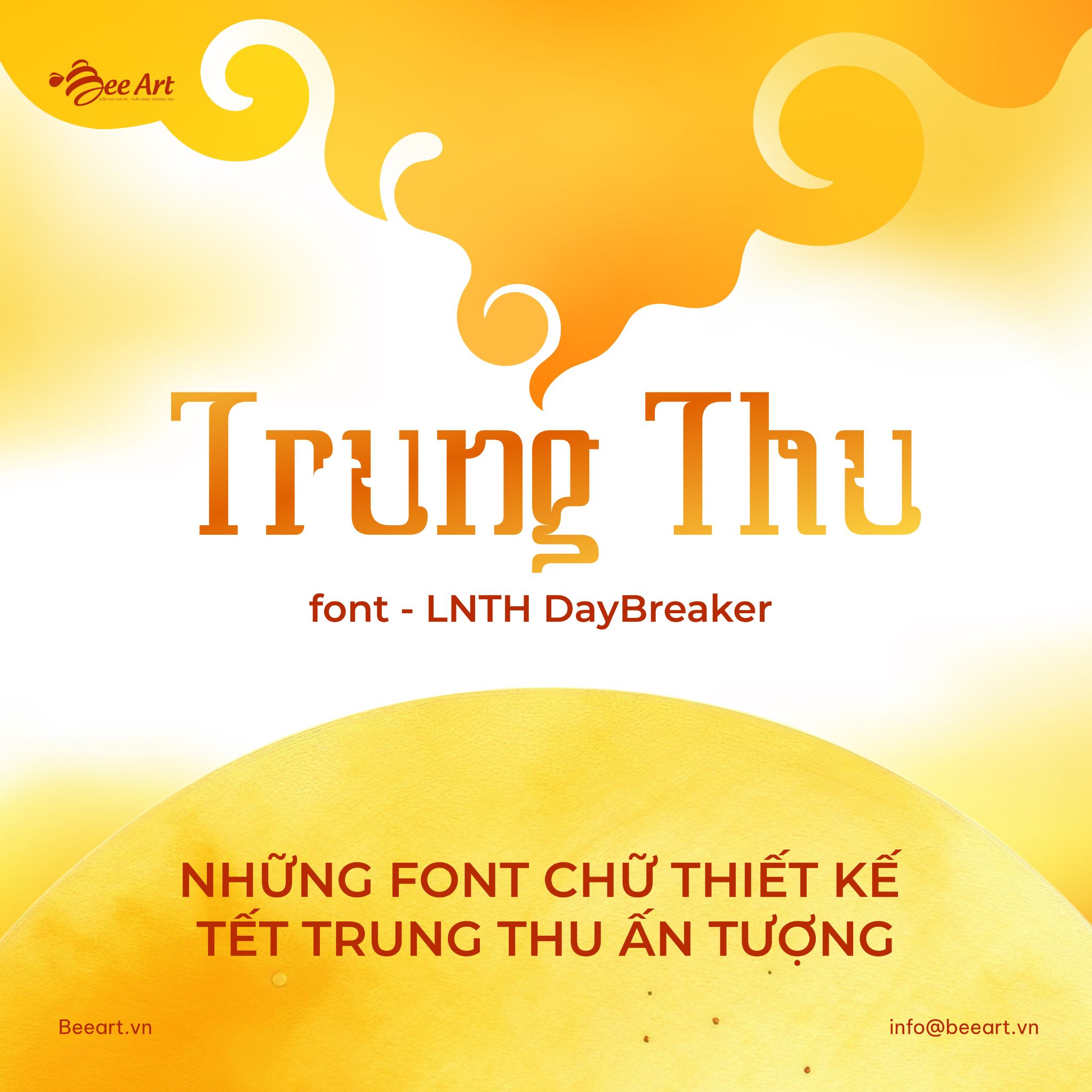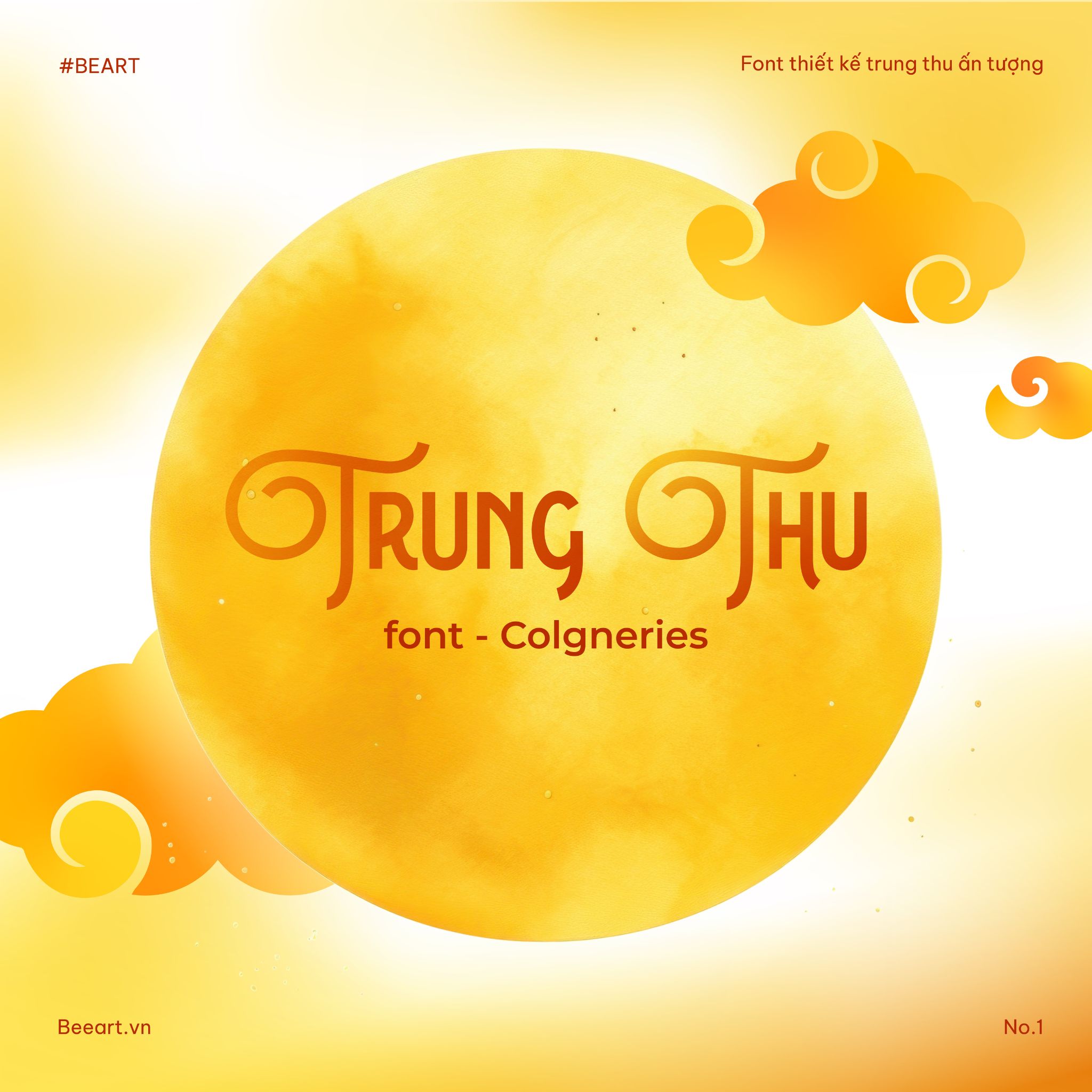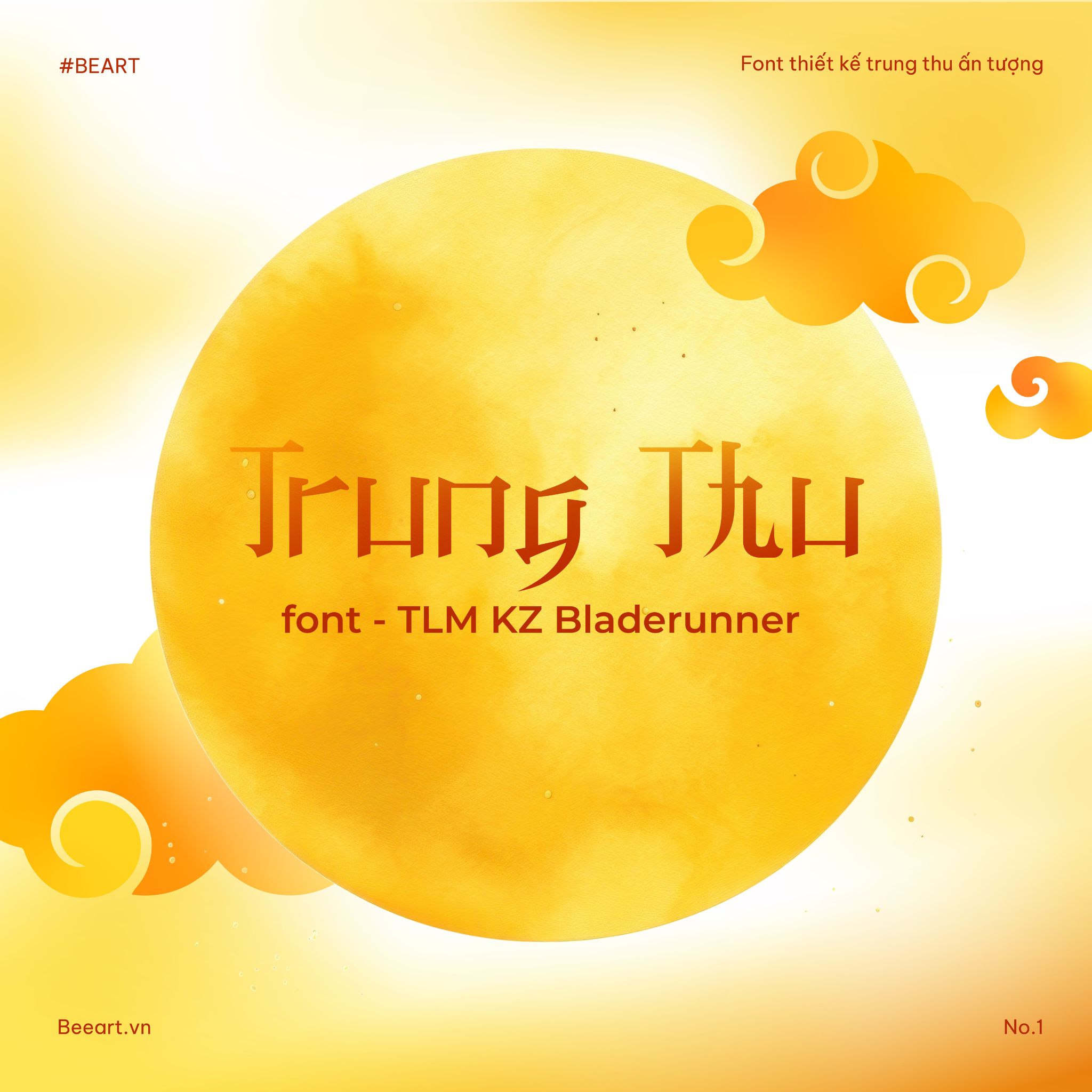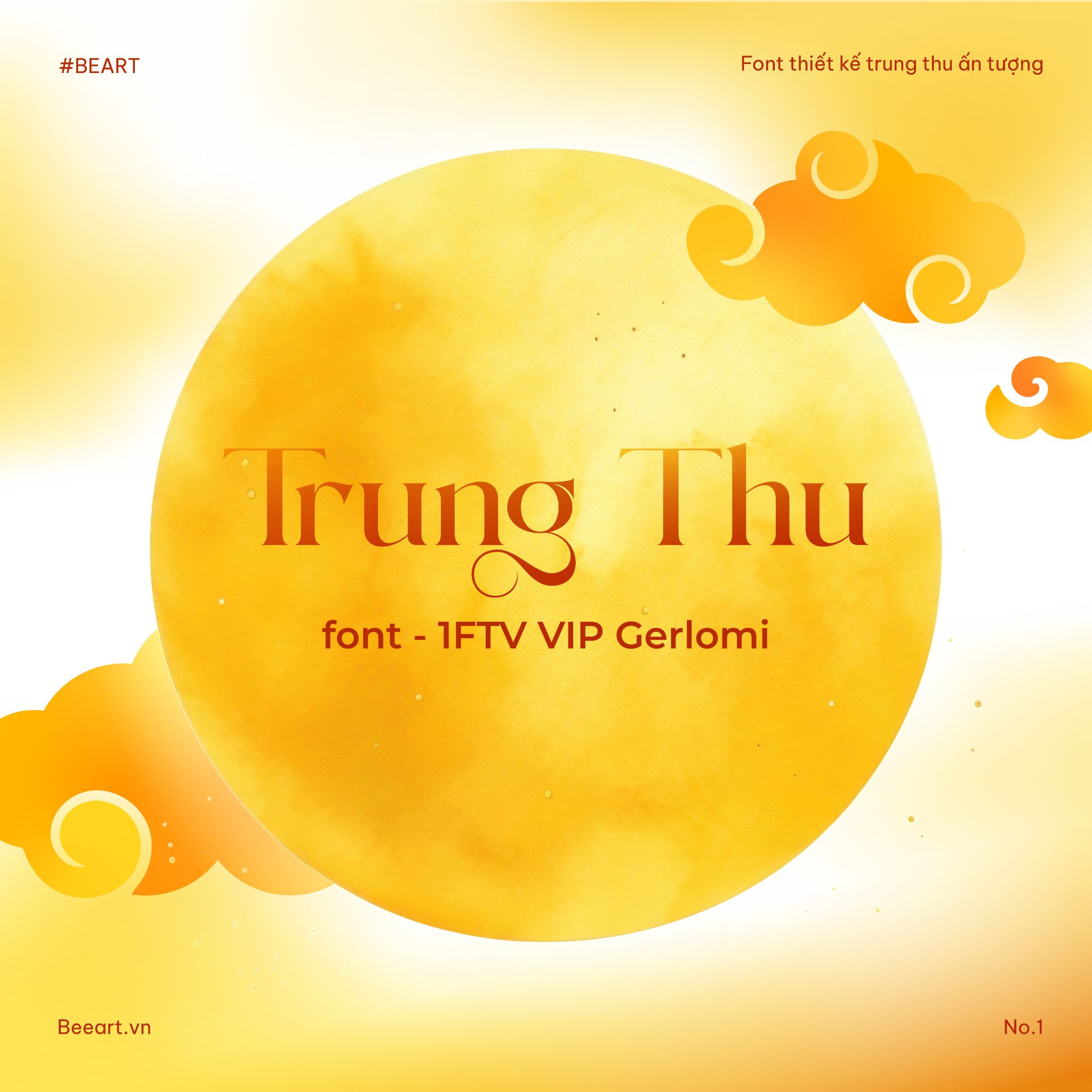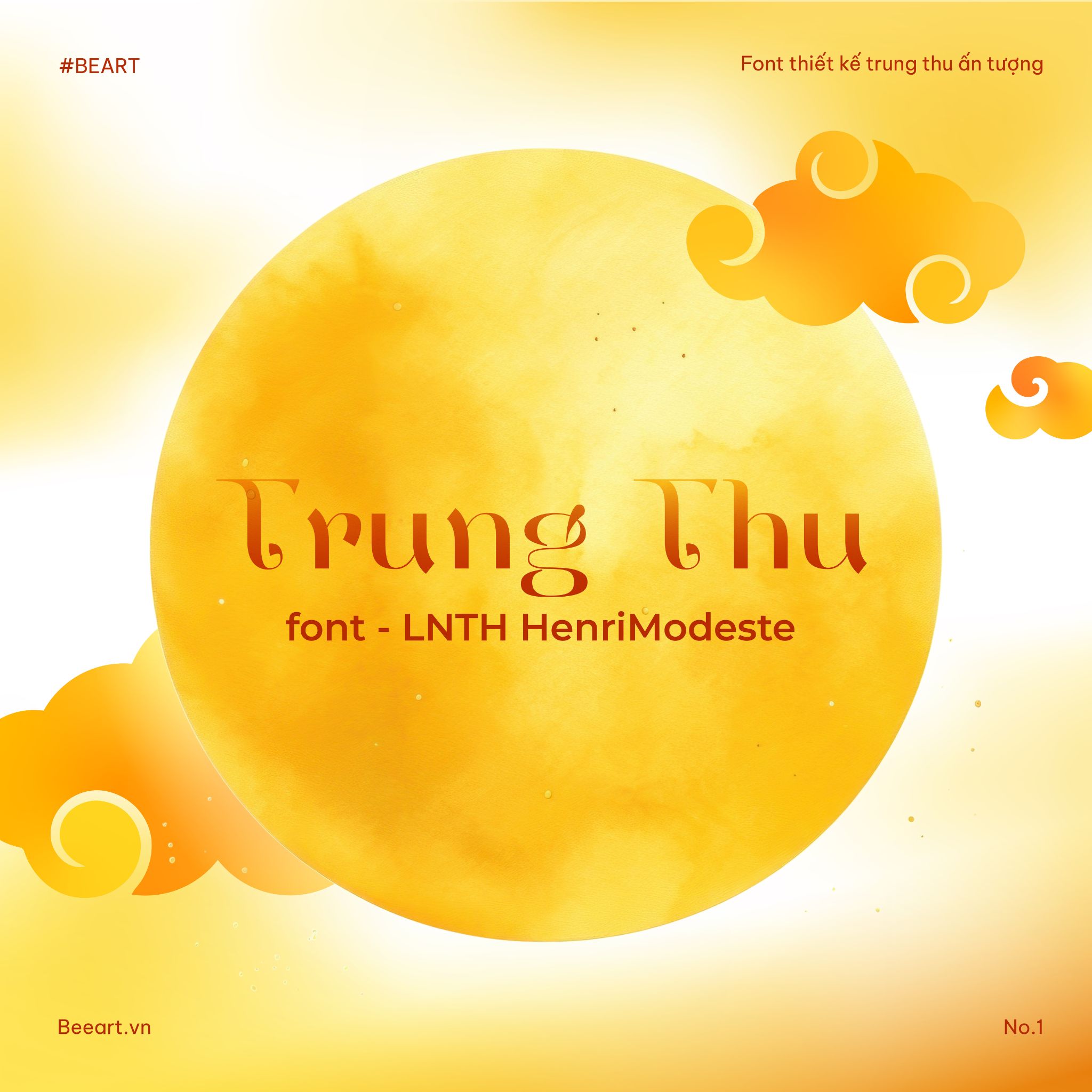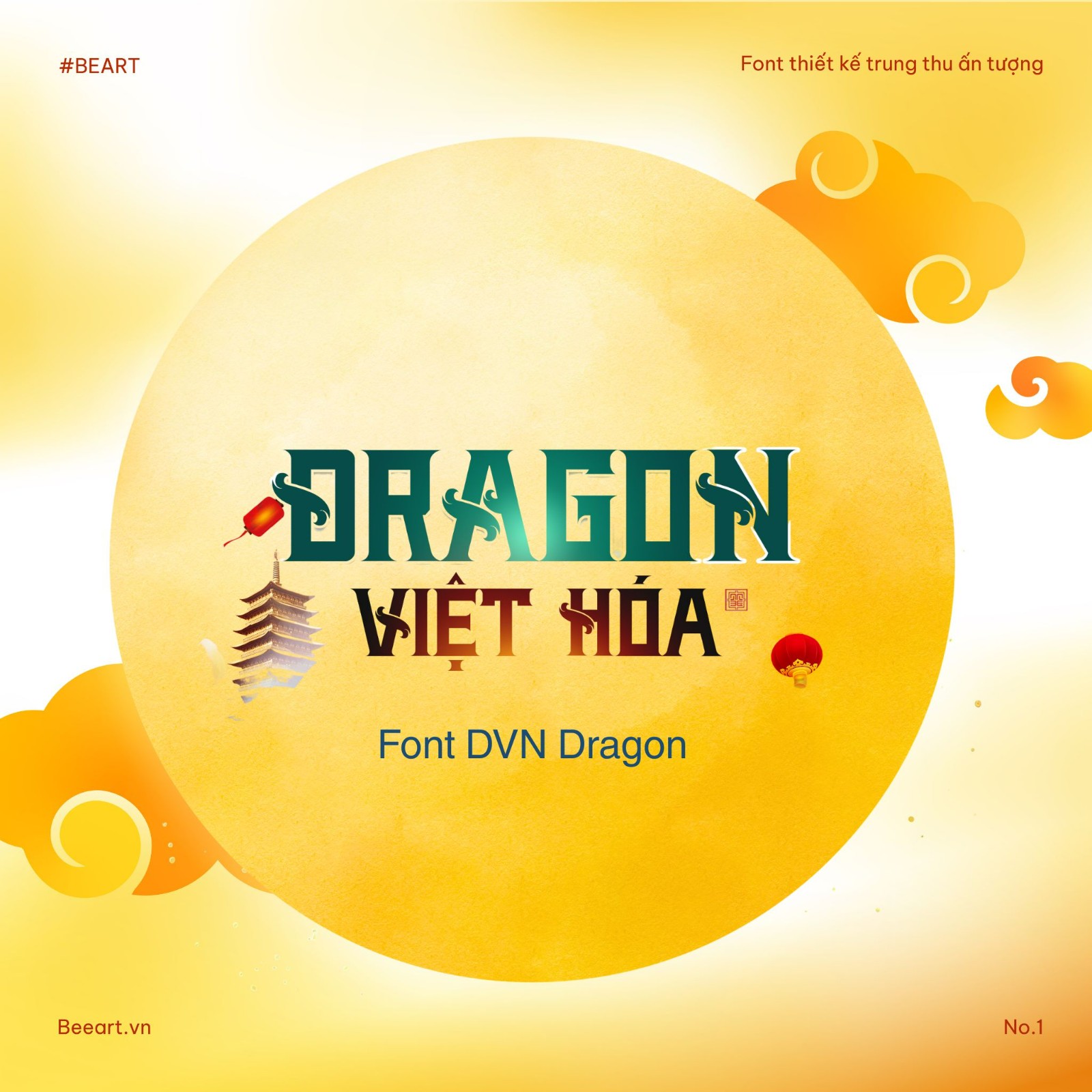
Mách bạn 11 font chữ thiết kế bao bì Tết Trung thu cực đẹp
Những font chữ thiết kế bao bì Tết Trung thu đẹp và ấn tượng như LTNH DayBreaker, Colgneries,... sẽ là những lựa chọn cứu cánh designer cho mùa trăng năm nay.
Font chữ thiết kế bao bì Tết Trung thu
Trung Thu đang đến rất gần rồi, các designer đã chuẩn bị ý tưởng cho mùa trăng năm nay chưa? Nếu bạn vẫn còn băn khoăn trong việc lựa chọn font chữ phù hợp cho những thiết kế bao bì hay ấn phẩm Trung thu, thì đây chính là gợi ý dành cho bạn. Hãy cùng Bee Art khám phá 11 font chữ Việt hóa độc đáo giúp thiết kế bao bì Tết Trung thu của bạn nổi bần bật trên mọi mặt trận.
Lưu ý khi chọn font chữ thiết kế bao bì Tết Trung thu 2025
Không khí mùa Tết Trông Trăng đang dần nhộn nhịp, và đây cũng là lúc các thương hiệu đẩy mạnh ra mắt sản phẩm quà tặng cùng nhiều hoạt động truyền thông nổi bật. Một trong những yếu tố quyết định sự thành công của bao bì chính là font chữ - chi tiết nhỏ nhưng có sức ảnh hưởng lớn đến cảm nhận của khách hàng. Để thiết kế vừa đẹp vừa hiệu quả, bạn cần lưu ý một số điểm sau khi lựa chọn font chữ.
Phân cấp rõ ràng giữa các nhóm thông tin
Khi thiết kế bao bì Tết Trung thu, không phải nội dung nào cũng nên dùng chung một kiểu font. Việc phân cấp thông tin không chỉ giúp bố cục trở nên hài hòa mà còn khiến người xem dễ theo dõi và tổng quan thiết kế cũng “nịnh” mắt hơn.
Phân cấp thông tin font chữ thiết kế bao bì Tết Trung thu
• Tiêu đề, tên bộ sưu tập hoặc tên sản phẩm: Đây là yếu tố cần được làm nổi bật nhất trên bao bì. Hãy chọn font chữ có cá tính, mang tính cách điệu vừa đủ để tạo sự khác biệt nhưng vẫn giữ được nét tinh tế. Với thiết kế bao bì Tết Trung thu, font chữ nên gợi lên cảm giác ấm áp, đoàn viên và sang trọng - vừa phù hợp tinh thần lễ hội, vừa giúp sản phẩm trông cao cấp và chuyên nghiệp hơn.
• Thông tin chi tiết về sản phẩm (nguyên liệu, trọng lượng, hướng dẫn bảo quản…): Hãy ưu tiên font sans-serif hoặc serif đơn giản, dễ đọc, để đảm bảo tính rõ ràng, bố cục khoa học và tạo cảm giác chuyên nghiệp.
Một hệ thống phân cấp hợp lý sẽ giúp bao bì vừa gọn gàng vừa tinh tế, đồng thời mang lại cảm nhận rất riêng cho khách hàng về sản phẩm cũng như hình ảnh thương hiệu.
Độ hòa hợp cùng màu sắc và chất liệu thiết kế
Trong thiết kế bao bì, font chữ không chỉ là phương tiện truyền tải thông tin, mà còn góp phần tạo nên cảm xúc tổng thể của sản phẩm. Chính vì vậy, font chữ thiết kế bao bì Tết Trung thu cần được đặt trong mối quan hệ hài hòa với màu sắc và chất liệu.
Một font serif cổ điển, khi kết hợp cùng gam màu ánh kim và in ép nổi trên giấy mỹ thuật cao cấp, sẽ gợi lên sự sang trọng, tinh tế, rất phù hợp với những hộp quà cao cấp dành tặng đối tác, khách hàng hay bạn bè. Ngược lại, một font brush mềm mại trên hộp kraft kết hợp cùng tông màu trầm ấm lại tạo nên cảm giác thân thuộc, gần gũi, thích hợp cho những hộp quà dành tặng gia đình và những người thân yêu.
Độ hòa hợp với màu sắc của font chữ thiết kế bao bì Tết Trung thu
Nếu sự phối hợp giữa font, màu sắc và chất liệu không đồng nhất, tổng thể bao bì sẽ mất đi sự hòa hợp. Ví dụ, một font chữ hiện đại, phá cách nếu đặt trên nền giấy truyền thống hoặc màu sắc cổ điển sẽ khiến thiết kế trở nên “lệch pha”, làm giảm đi giá trị thẩm mỹ và trải nghiệm thị giác.
Do đó, khi thiết kế bao bì Tết Trung thu 2025, nhà thiết kế cần cân nhắc font chữ như một phần của bức tranh tổng thể, để mỗi chi tiết đều được trau chuốt, tỉ mỉ nhất.
Thể hiện phần nào thông điệp truyền tải
Mỗi font chữ đều có một “tính cách” riêng, có font mang vẻ mạnh mẽ, dứt khoát; có font lại nhẹ nhàng, tinh tế; cũng có font gợi sự vui tươi nhí nhảnh. Trong thiết kế bao bì Tết Trung thu, font chữ không chỉ để làm đẹp mà còn góp phần nói lên thông điệp thương hiệu muốn gửi gắm.
Nếu bộ sưu tập hướng đến phân khúc cao cấp, font chữ sang trọng, chuẩn mực sẽ giúp tôn lên đẳng cấp. Ngược lại, với những thiết kế mang tinh thần gắn kết gia đình hay gần gũi với trẻ nhỏ, font mềm mại, bo tròn sẽ tạo cảm giác ấm áp và thân thiện hơn. Việc chọn đúng font chính là chìa khóa để bao bì vừa đẹp mắt, vừa truyền tải trọn vẹn tinh thần mà thương hiệu mong muốn.
Đảm bảo tính dễ đọc và khả năng ứng dụng
Trong thiết kế bao bì Tết Trung thu, font chữ không chỉ cần đẹp mà còn phải dễ đọc. Bao bì thường chứa nhiều lớp thông tin: từ tên thương hiệu, tên bộ sưu tập cho đến mô tả chi tiết về sản phẩm. Nếu font quá cầu kỳ, khách hàng có thể khó tiếp nhận thông tin, đặc biệt khi chữ được in ở kích thước nhỏ.
Font chữ thiết kế bao bì Tết Trung thu đảm bảo tính dễ đọc và khả năng ứng dụng
Bên cạnh đó, chất liệu bao bì rất đa dạng: Giấy mỹ thuật, hộp nhũ, hộp kim loại hay kraft thô mộc, và mỗi chất liệu sẽ tác động khác nhau đến độ hiển thị của font. Một font có khả năng ứng dụng linh hoạt, giữ được độ rõ nét và cân bằng thẩm mỹ trên nhiều bề mặt chính là lựa chọn lý tưởng. Nhờ đó, thiết kế bao bì không chỉ đẹp trong mắt nhìn mà còn tiện dụng, bền vững và mang lại trải nghiệm trực quan tốt nhất cho khách hàng.